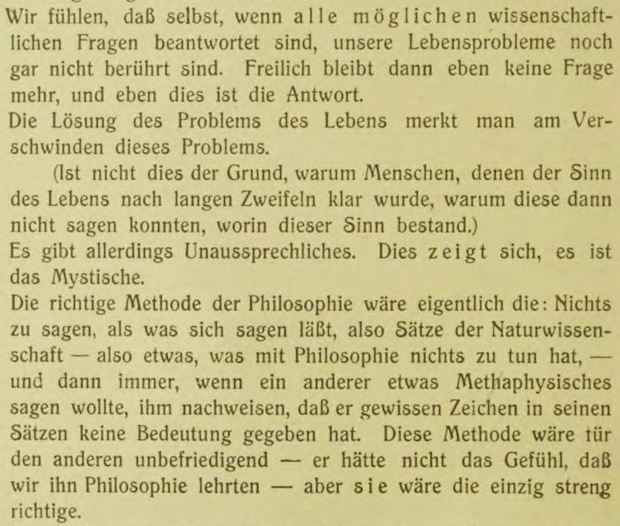
Logisch-Philosophische Abhandlung, 1921
kennt Ihr die Schrift im beigefügten Muster? Sie kommt aus der Erstausgabe von Wittgensteins Tractatus. Vielen Dank im Voraus.
Ja, an die dachte ich auch zuerst, ähnlich ist sie, hat aber noch eine deutlicher ausgeprägte Jugendstil-Anmutung (z. B. W, M, U, S, s).
Ich denke irgendwas aus 1900–1915 … Edwardian hat viele Elemente davon (U, s …)